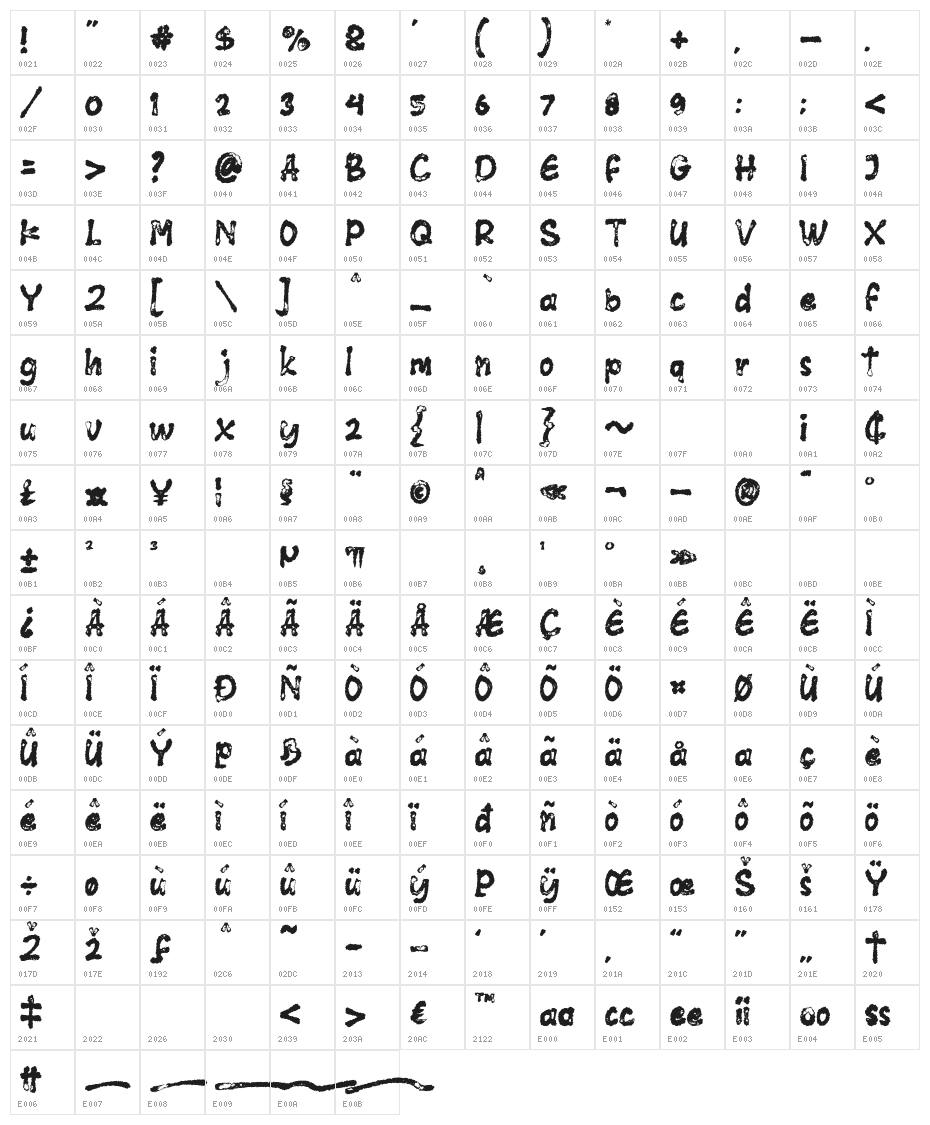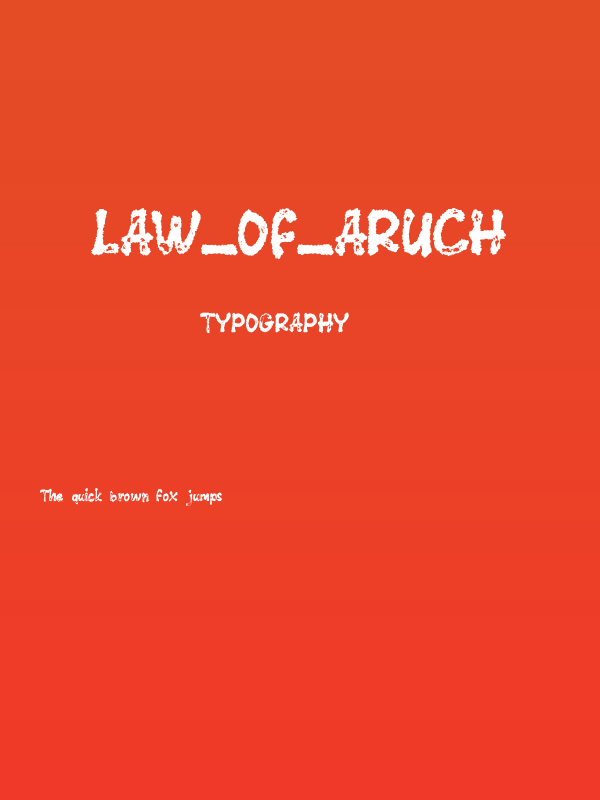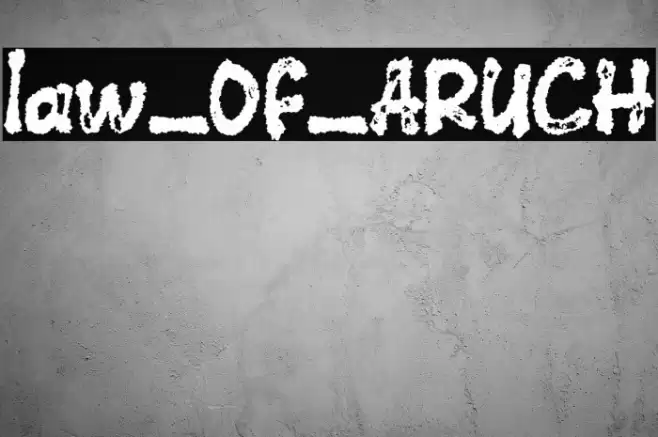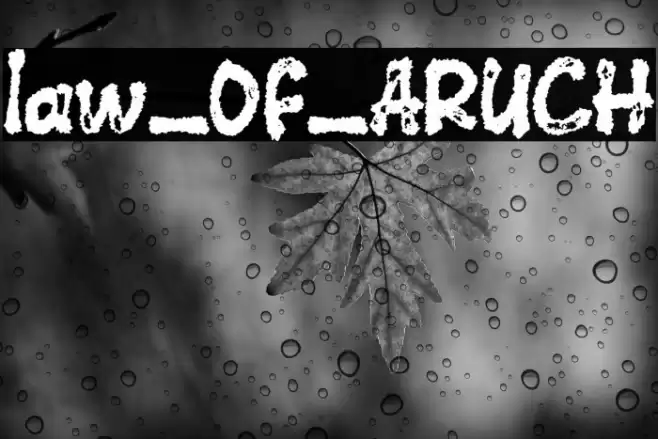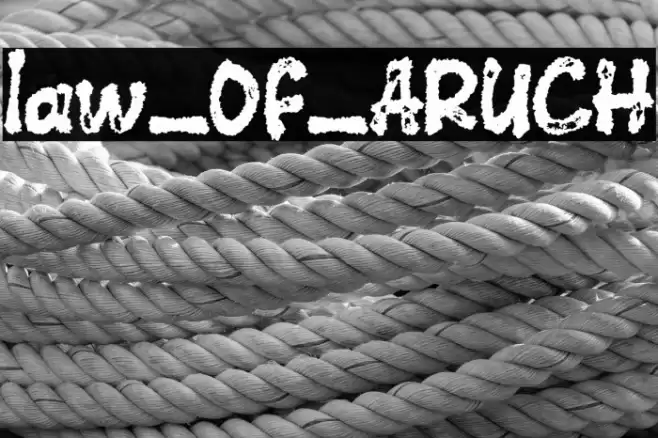
law_OF_ARUCH Font
| Progetti proposti | Ideal for corporate branding, digital interfaces, and editorial design due to its clarity and modern appeal. |